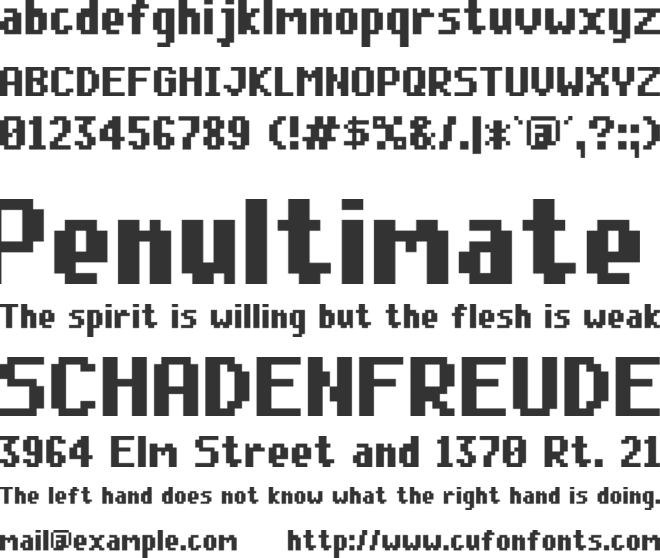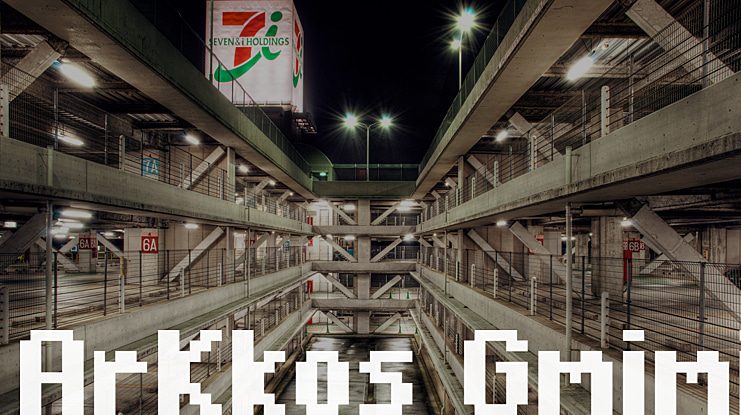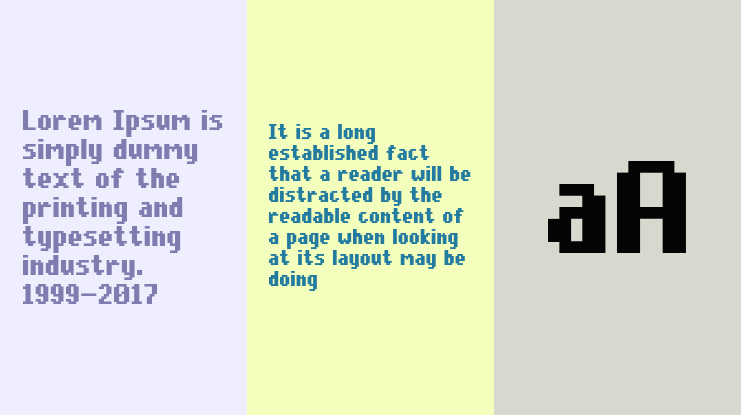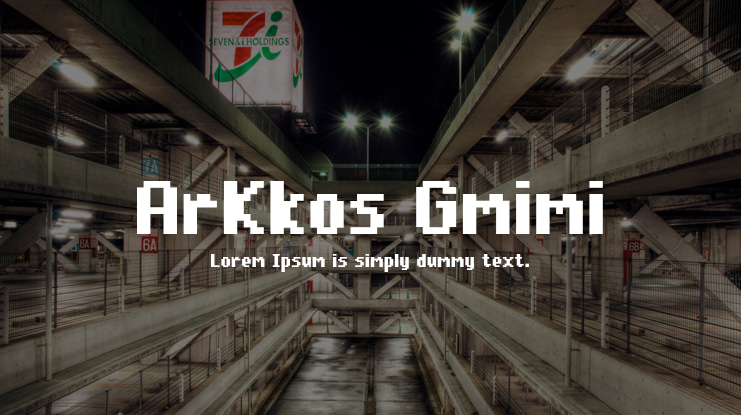
ArKkos Gmimi Font
Police inspirée de mon premier lecteur MP3.
Idéal Wordart, affiche...
Font inspired by my first MP3 player.
Ideal Wordart, poster ...